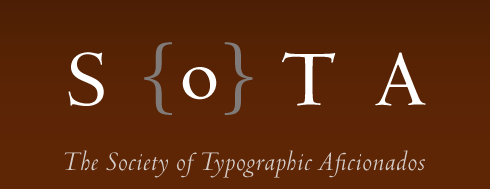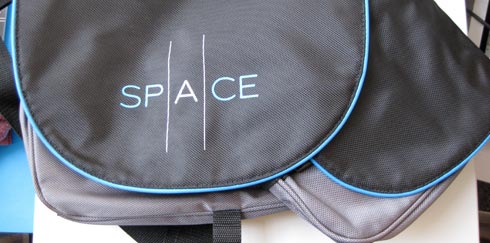
Wahl zum Goldenen Windbeutel 2010 ist eröffnet
Foodwatch wird dieses Jahr zum 2. Mal den »Goldenen Windbeutel« für die dreisteste Food-Werbelüge verleihen (Fontblog über die Wahl 2009 Wer verdient den Goldenen Windbeutel? und den damaligen Gewinner). Eine prominente Jury hat aus elf Produkten, die seit dem Goldenen Windbeutel 2009 auf www.abgespeist.de neu hinzugekommen sind, fünf nominiert. Nun entscheiden die Verbraucher, wer die unrühmliche Trophäe überreicht bekommt. Zur Auswahl stehen:
• Beo Heimat Apfel-Birne von Carlsberg
• Bertolli Gegrilltes Gemüse von Unilever
• Der Gelbe Zitrone-Physalis von Pfanner
• Duett Champignon Creme-Suppe von Escoffier
• Monte Drink von Zott
Weiter Informationen über die 5 Produkte und warum sie nominiert wurden auf Page online. Fast interessanter als die 5 Nominierten ist ein Blick in die komplette Liste der Lebensmittel, die so gesund sein wollen, es aber meist nicht sind. Das 3-seitige PDF (Abb. oben links)  mit den 24 Produkten liegt hier zum Download bereit.
Neu im Fontblog: der Stern der Woche, immer dienstags. Er löst das Produkt der Woche (PdW) ab. Heute ist unser die TYPO-Tasche 2009. Eigentlich sind es zwei Taschen, denn im Inneren der »Space«-Tasche steckt die kleiner Krimskrams-Tasche. Wie jede unserer Konferenztaschen wurde auch diese eigens für die TYPO entworfen und angefertigt (Design: Studio Adhoc). Das heißt: Es gibt nicht viele davon. Und wer sie trägt, ist ein ★.
Neuer Wettbewerb: SOTA Catalyst Award
Die Society of Typographic Aficionados (SOTA), Veranstalter der jährlichen Typografie-Konferenz TypeCon, hat einen neuen Wettbewerb ins Leben gerufen. Der Catalyst Award wendet sich an junge Designer unter 30, die Außergewöhnliches in den Bereichen Schriftentwurf, Schriftgeschichte oder anderen typografischen Gebieten geleistet haben. Der Empfänger des Cataylst-Awards erhält eine Einladung zur kommenden TypeCon nach Los Angeles (17. – 22. August 2010), wo er seine Arbeit vor einem Fachpublikum präsentieren kann. Darüber hinaus winkt ein Taschengeld zur Deckung der Reisekosten von 1500 US-Dollar.
MoMA »kauft« @-Zeichen
Wie das New Yorker Museum of Modern Art heute in seinen Hausmitteilungen Inside/Out berichtet, hat die Abteilung Architecture and Design das @-Zeichen in seine Sammlung aufgenommen. »Es ist ein bedeutsamer und ermutigender Erwerb, der uns alle stolz macht.« heißt es auf der Internetseite des Museums. Doch was bedeutet die Anschaffung eines Schriftzeichens überhaupt, sowohl konzeptionell als auch praktisch?
Das MoMA erläutert seine historische Entscheidung so: »Der Erwerb des @-Zeichens geht einen Schritt weiter als alle Akquisitionen der jüngeren Zeit. Er fußt auf der Annahme, dass der physische Besitz eines Objekts keine Voraussetzung mehr für seine Anschaffung ist. Dies ebnet uns Kuratoren einen völlig neuen Weg zum Taxieren der Welt und erlaubt uns Dinge anzuerkennen, die eigentlich ›nicht zu haben‹ sind – weil sie entweder zu groß sind (Gebäude, eine Boeing 747, Satelliten, …) oder weil sie einfach nur da sind und allen und niemandem gehören, wie das @. Solche Exponate müssen sich den gleichen Kriterien von Qualität, Relevanz und Einzigartigkeit stellen wie die übrigen Objekte der MoMA-Kollektion.«
Um zu verstehen, warum da MoMA das @-Zeichen in seine Sammlung aufgenommen hat, hilft ein Blick in die Geschichte des Symbols. Die meisten von uns kannten es als Affenschaukel, Klammeraffe oder Elefantenohr, bevor es als essenzieller Bestandteil von E-Mail-Adressen »lebensnotwendig« wurde. In dieser (neuen) Rolle trennt es den Benutzer- vom Domainname.
Es gibt mehrere Theorien über die Entstehung des @. Zwei davon sind im Mittelalter angesiedelt, wo es entweder als handschriftliche Verschmelzung (Ligatur) der Buchstaben a und d des lateinischen Wortes »ad« (deutsch »zu«, »zu etwas hin«) diente, oder aber als Abkürzungszeichen, beispielsweise nach einem Brief eines römischen Kaufmannes über Schiffsladungen als Abkürzung für das Wort »Amphore«.
Nach gängiger Typografen-Meinung ist das @ eine Ligatur, die schon zu Bleisatzzeiten in der Monotype-Bibliothek Mitte des 19. Jahrhunderts auftauchte. Seit den 1880er Jahren ist es auf englischen Schreibmaschinen nachgewiesen. Dabei handelte es sich um ein angelsächsisches kaufmännisches Wertzeichen, dessen Bedeutung aus der Preisangabe »five apples at 10 pence« = »5 apples @ 10 p« hervorging. In den deutschen Sprachraum wurde parallel dazu das französische à eingeführt, zum Beispiel für »5 Brötchen à 10 Pfennig«.
* Below the line (engl. für unter der Linie, Abk. BTL) bezeichnet im Marketing alle »nicht-klassischen« Werbe- & Kommunikationsmaßnahmen, zum Beispiel Promotion-Team-Aktionen und nicht für jedermann erkennbare Aktionen, die Zielgruppen direkt und persönlich ansprechen.